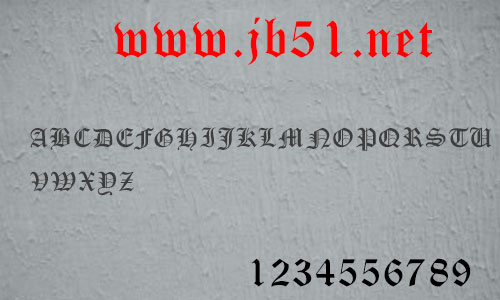
Old English Five英文哥特式字體,字體筆觸粗細(xì)適中,書寫流暢,具有很好的視覺(jué)感,適合應(yīng)用于藝術(shù)設(shè)計(jì)、平面宣傳設(shè)計(jì)、網(wǎng)頁(yè)設(shè)計(jì),書法字帖等領(lǐng)域,需要的朋友快來(lái)本站下載使用吧!